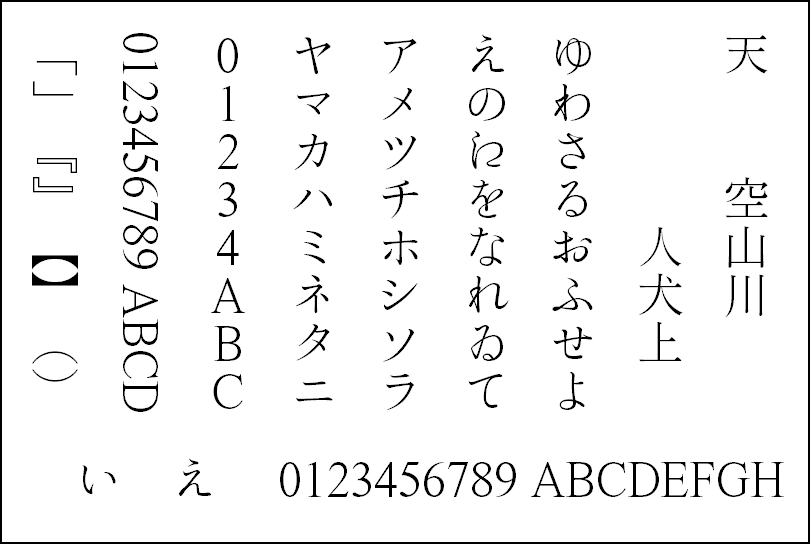
錦明朝かな
「錦(にしき)明朝かな」は、明朝体の仮名文字専用フリーフォントです。CID-keyed OpenType/CFF形式で作られています。
現行版では、次のUnicode値の範囲のグリフ(文字図形)を収録しています。
- ひらがな: 3041..3096, 3099..309F, 1B001(含・半濁点付きか行等)
- カタカナ: 30A1..30FF, 31F0..31FF, 1B000(含・半濁点付きカ行等)
オールドスタイルの仮名で、ウェイトはMS 明朝とだいたい合うようにしてあります。
Version 1.110からの変更点
- 字面が小さすぎるグリフに対する修正。
- 小さい仮名をボックスの外側へ4%移動。
- ひらがな「あ」のグリフを変更(見本帳から離れ、3画目の始まりを2画目と離す形へ)。
- ひらがな「そ」のグリフを変更(見本帳通り、1画目と2画目とを繋げた形へ)。
- ひらがな「ま」のグリフを変更(見本帳から離れ、1画目が2画目より長い形へ)。
- 他、グリフの調整。
今後の検討課題
横書き用のプロポーショナルメトリクス情報 (palt) の付加。Version 1.110で済。
- 字形の改良。
長期的目標として、漢字グリフも作って「仮名フォント」から「日本語フォント」にしたいという野望もあるのですが、作業量の膨大さの前に実現する見込みは今のところ立っていません。
- 東京築地活版製造所(大正四)『五號明朝活字總數見本 全』